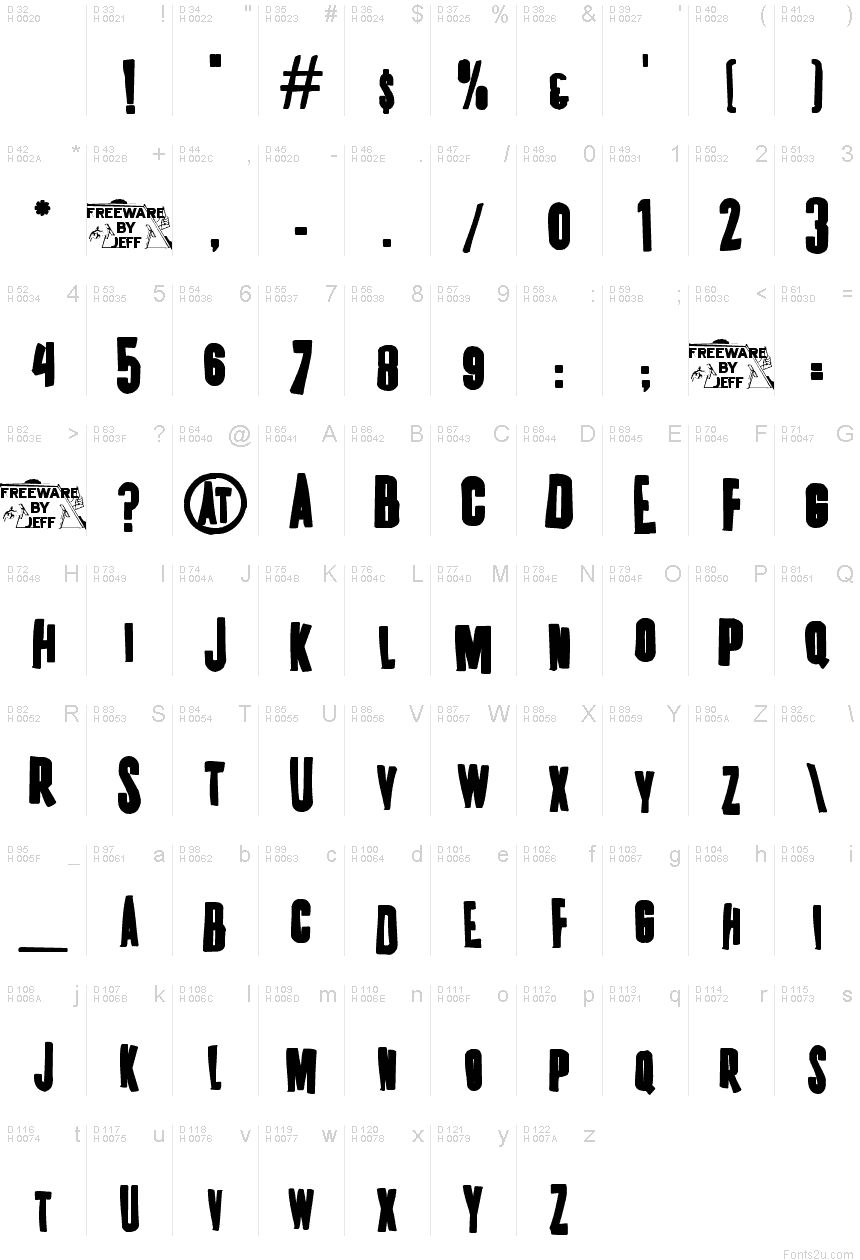
K.P. Duty - Frazzled JL von Jeffrey N. Levine ist eine kostenlose Comic-Display-Schriftart mit einer herrlich überkoffeinierten Ausstrahlung. Schwere, tintige Formen wackeln und wölben sich ineinander, was jedem Wort eine nervöse, handgeschnittene Energie verleiht, als käme es direkt aus einem Zine oder einem Underground-Konzertplakat. Die Buchstaben drängen sich zu einer dichten, schwarzen Masse zusammen – für eine Botschaft, die laut, fett und ein wenig durchgeknallt rüberkommt.
Mit K.P. Duty - Frazzled JL schreien Titel förmlich von der Seite. Perfekt für Poster, Plattencover, Zines, Parodie-Comics, Game-Splash-Screens und freche Social-Media-Grafiken. Diese kostenlose Schrift glänzt, wenn man sie groß einsetzt und den begleitenden Text in einer schlichten serifenlosen Schrift hält. So lassen die klobigen, ausgefransten Formen die Attitüde sprechen, während der Rest sauber und lesbar bleibt.
K.P. Duty - Frazzled JL
Jeffrey N. Levine
A non-conforming sans serif, varying in height and stroke width. Based on the title lettering on the Elvis Presley soundtrack album "G.I. Blues"...and "grunged up" with the help of Ray Larabie.